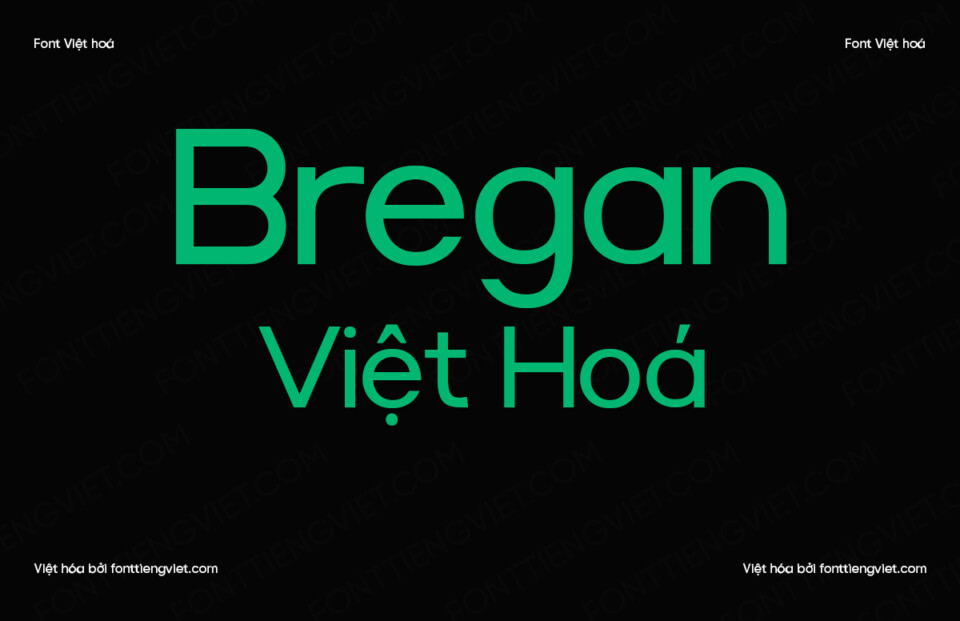
Font Việt hóa 1FTV VIP Bregan Regular
Font Việt hóa 1FTV VIP Bregan Regular – Bộ Font Chữ Nghệ Thuật Đẳng Cấp Cho Thiết Kế
Giới thiệu về bộ Font Việt hóa 1FTV VIP Bregan Regular
Trong thế giới đồ họa hiện đại, việc lựa chọn một Font Miễn Phí chất lượng luôn là ưu tiên hàng đầu của các nhà thiết kế chuyên nghiệp lẫn người mới bắt đầu. Font Việt hóa 1FTV VIP Bregan Regular nổi lên như một hiện tượng nhờ sự kết hợp hoàn hảo giữa nét cổ điển và hơi thở đương đại. Đây là bộ phông chữ được tinh chỉnh kỹ lưỡng về dấu tiếng Việt, giúp người dùng tại Việt Nam dễ dàng sử dụng trong các phần mềm thiết kế phổ biến như Adobe Photoshop, Illustrator hay Canva mà không lo lỗi hiển thị. Với cấu trúc chữ thanh thoát nhưng vẫn giữ được độ dày vừa phải, bộ font này mang đến sự sang trọng và uy tín cho mọi tác phẩm nghệ thuật. Cho dù bạn đang làm việc trên một dự án thương hiệu hay đơn giản là trang trí bài giảng, sự hiện diện của nó sẽ làm thay đổi hoàn toàn diện mạo sản phẩm của bạn.
Những đặc điểm nổi bật của Font Việt hóa 1FTV VIP Bregan Regular
Thiết kế tinh tế và chuyên nghiệp
Đặc điểm nhận dạng lớn nhất của Font Việt hóa 1FTV VIP Bregan Regular chính là các đường nét được trau chuốt tỉ mỉ. Các ký tự trong bảng chữ cái có sự cân đối về khoảng cách và chiều cao, tạo nên một nhịp điệu thị giác dễ chịu cho người xem. Khác với các font chữ phổ thông, phiên bản Regular này tập trung vào tính ứng dụng cao, giúp văn bản vừa dễ đọc vừa mang đậm tính nghệ thuật. Việc Việt hóa chuẩn xác giúp các dấu thanh không bị đè lên chữ, giữ nguyên cấu trúc thiết kế ban đầu của tác giả.
Khả năng ứng dụng đa dạng
Nhờ vẻ ngoài lịch lãm, Font Việt hóa 1FTV VIP Bregan Regular cực kỳ phù hợp cho các thiết kế tiêu đề, bìa sách, poster sự kiện hoặc menu nhà hàng cao cấp. Trong lĩnh vực giáo dục, giáo viên có thể sử dụng font này để tạo ra các slide bài giảng sinh động, thu hút sự chú ý của học sinh. Sự linh hoạt của nó cho phép người dùng biến hóa từ phong cách tối giản đến phong cách cầu kỳ mà không làm mất đi giá trị thẩm mỹ cốt lõi. Đây thực sự là một công cụ hỗ trợ đắc lực cho cộng đồng sáng tạo nội dung tại Việt Nam.
Lưu ý khi phối hợp màu sắc
Khi sử dụng Font Việt hóa 1FTV VIP Bregan Regular, việc kết hợp màu sắc đóng vai trò quan trọng. Do đặc tính nét chữ rõ ràng, bạn nên ưu tiên các màu sắc có độ tương phản tốt như đen trên nền trắng hoặc vàng đồng trên nền xanh đậm để làm nổi bật sự sang trọng. Tránh sử dụng quá nhiều hiệu ứng đổ bóng phức tạp vì bản thân cấu trúc chữ đã đủ sức hút. Hãy để sự đơn giản tôn vinh lên vẻ đẹp vốn có của bộ phông chữ VIP này.
Tổng kết về giá trị của Font Việt hóa 1FTV VIP Bregan Regular
Tóm lại, việc sở hữu Font Việt hóa 1FTV VIP Bregan Regular trong bộ sưu tập cá nhân là một quyết định đúng đắn cho bất kỳ ai yêu thích cái đẹp. Nó không chỉ giải quyết bài toán về hiển thị tiếng Việt mà còn nâng tầm chất lượng cho các dự án thiết kế. Một bộ Font Miễn Phí, Font Việt Hóa, Font Việt hóa 1FTV VIP Bregan Regular như thế này chính là món quà tuyệt vời dành cho cộng đồng designer Việt. Hãy tải về và bắt đầu sáng tạo ngay hôm nay để thấy sự khác biệt mà nó mang lại cho tác phẩm của bạn.